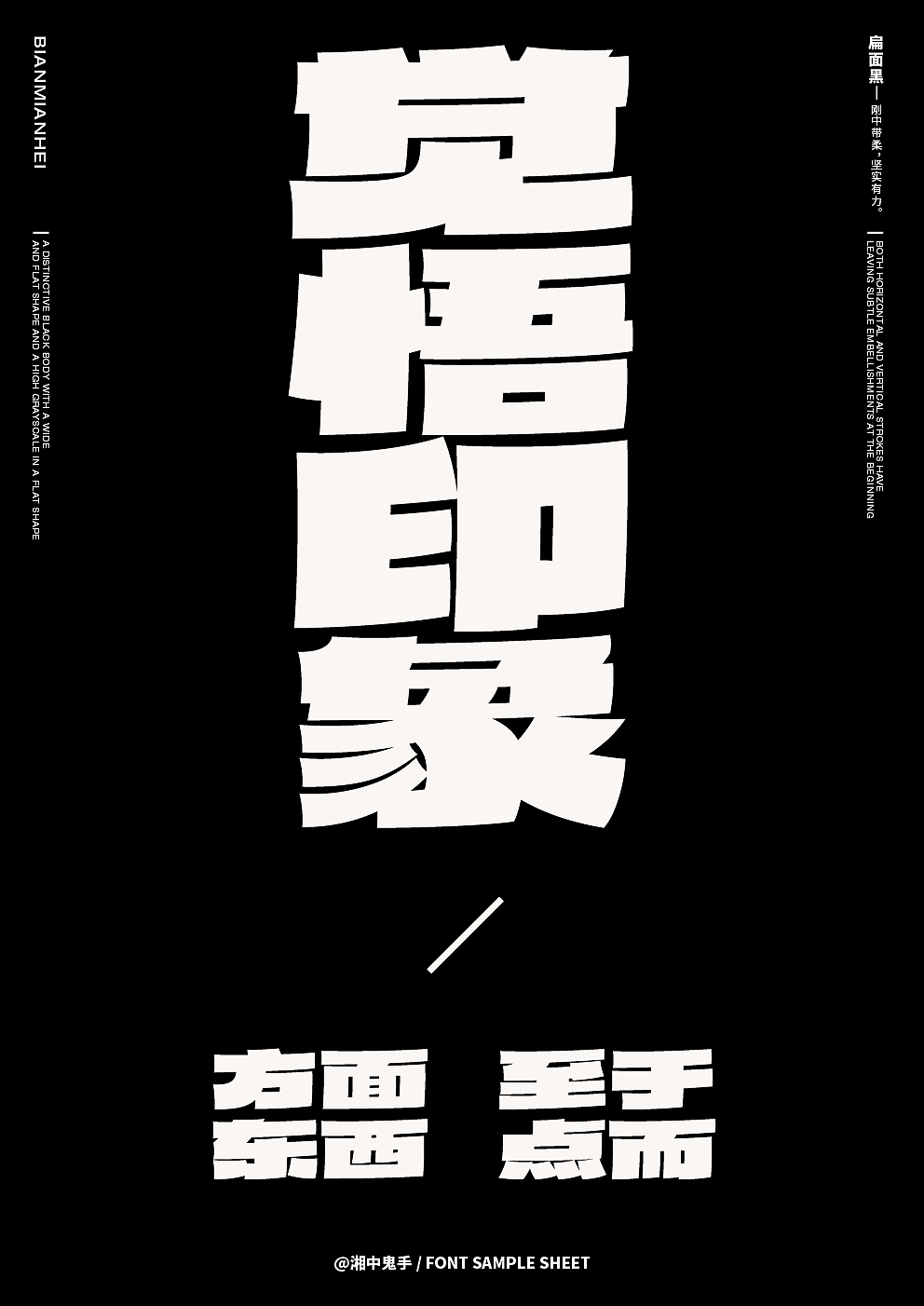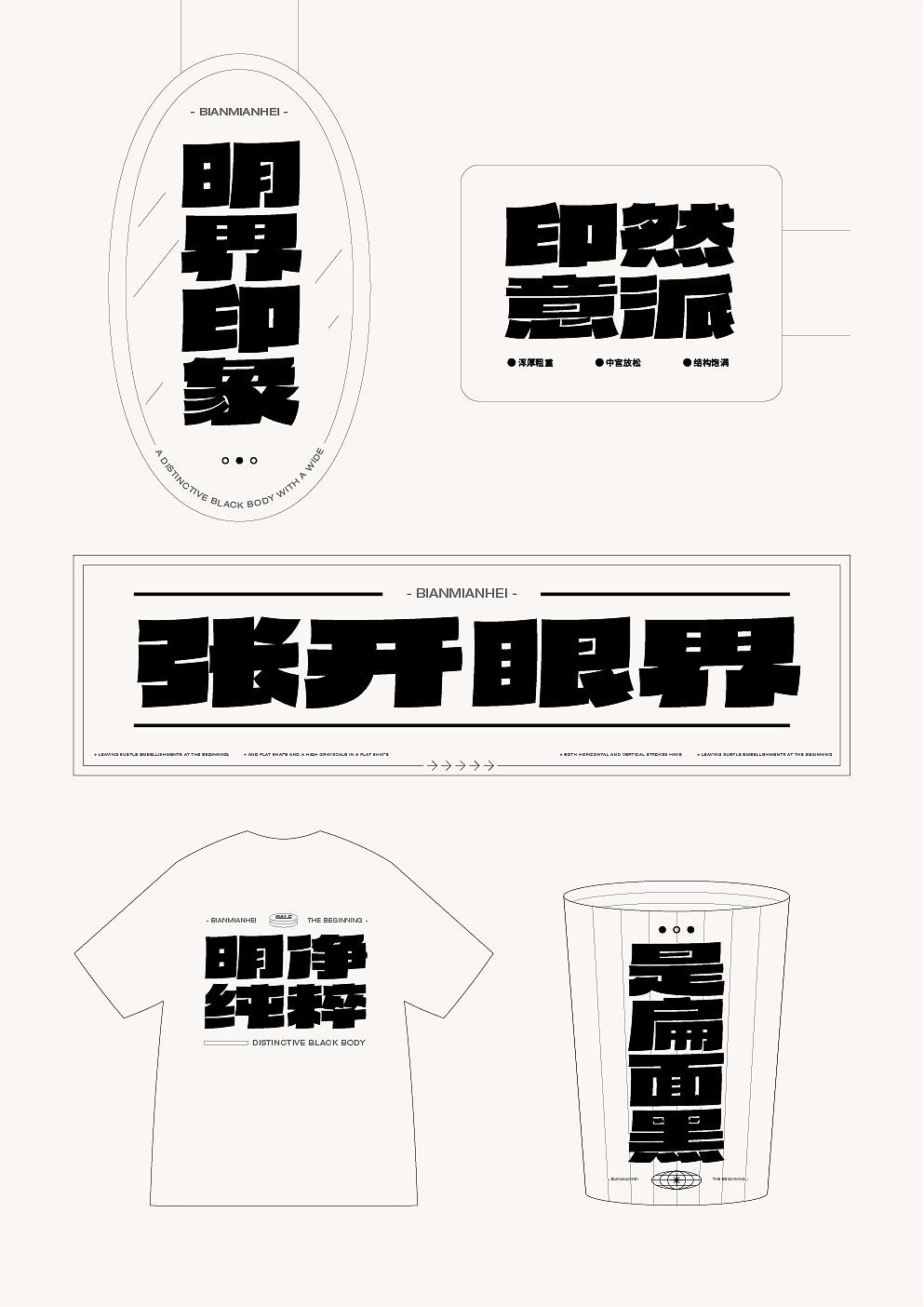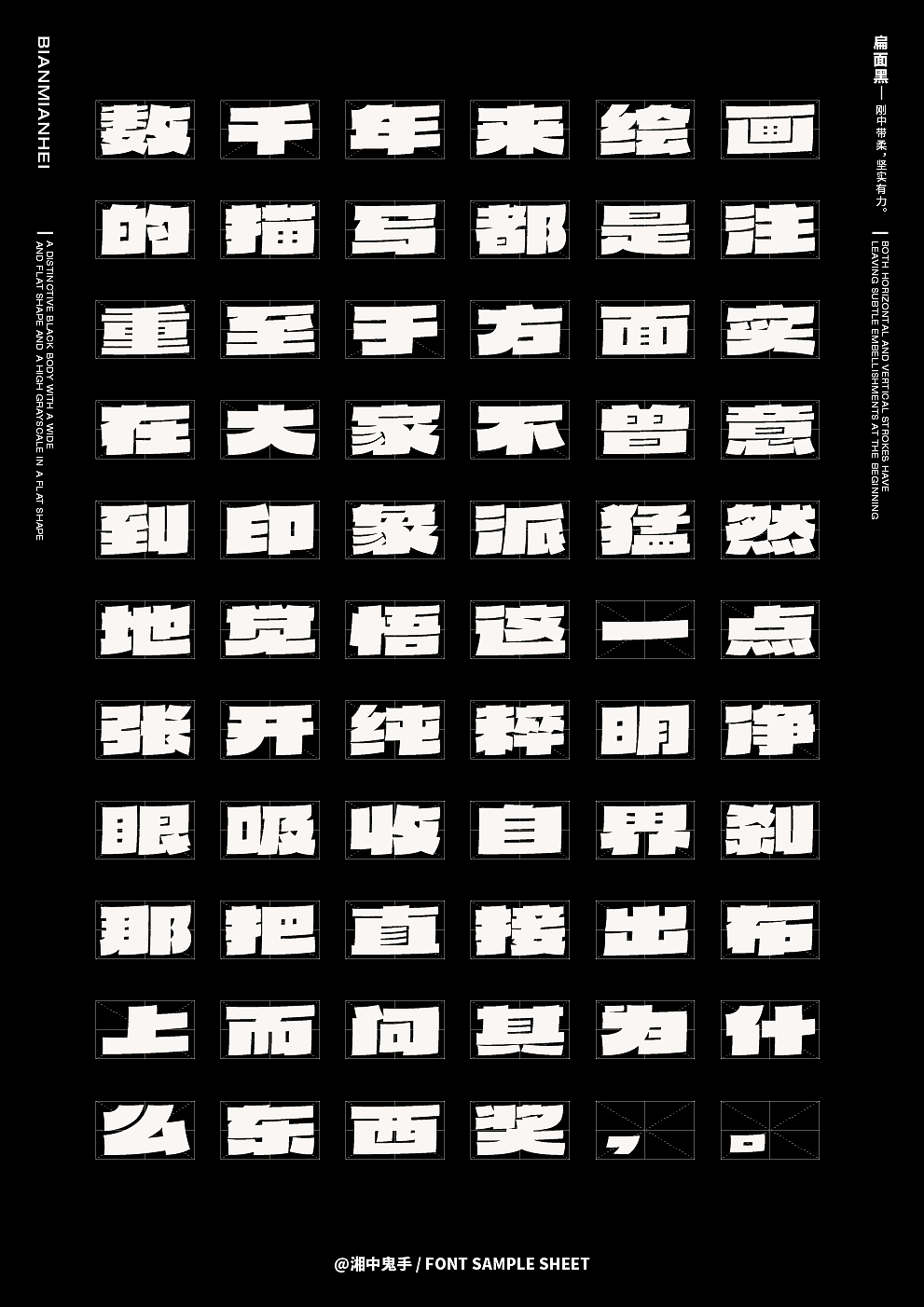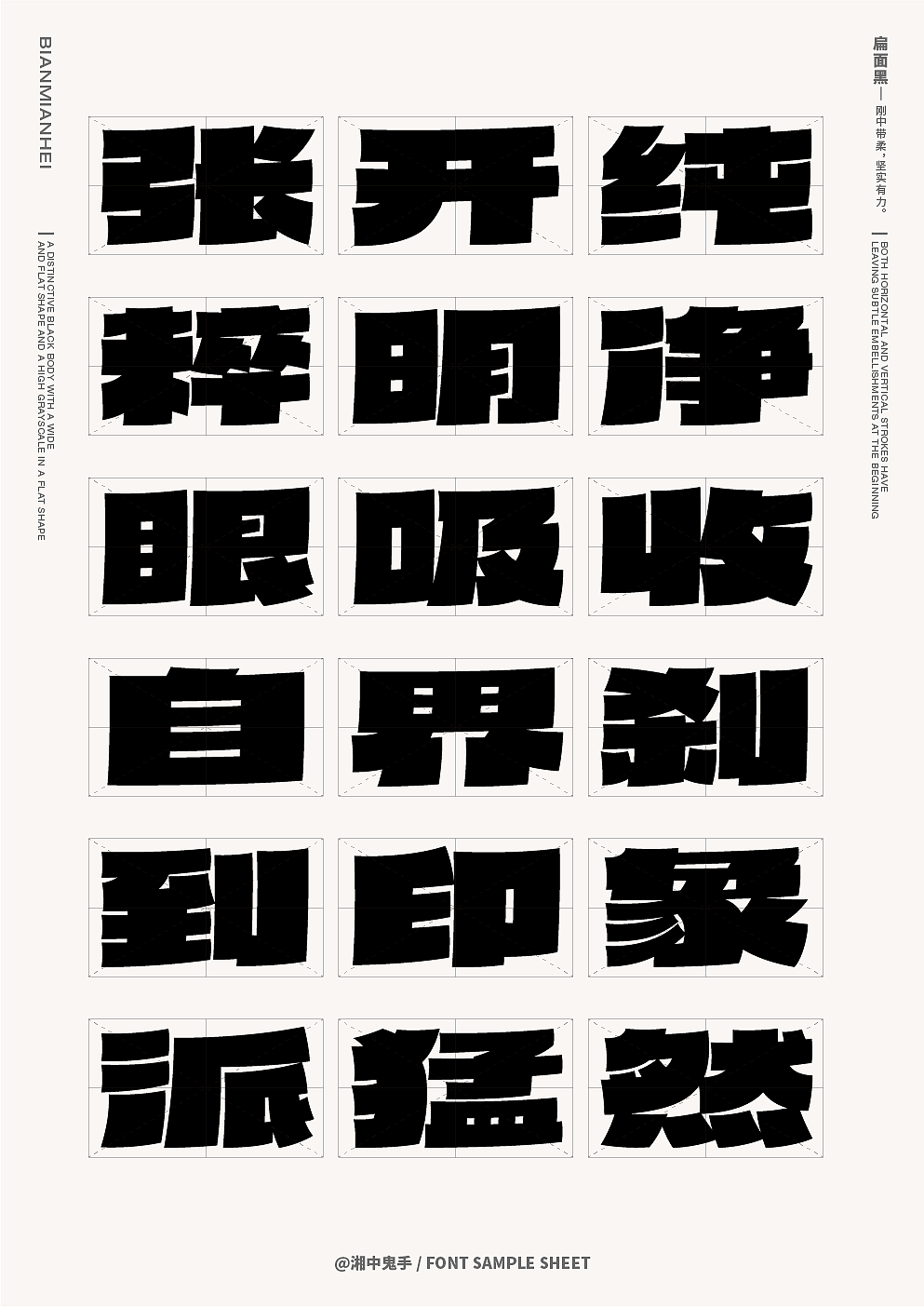
第12届『方正奖』中文专业组金奖:《扁面黑》
《扁面黑》
扁面黑是一款个性鲜明的黑体,其字形宽扁,灰度较高成面状,所以取名扁面黑;横竖笔画都略带曲线,起笔留有细微饰角,横竖笔画微微倾斜,整齐中平添一丝灵动,笔画浑厚粗重,中宫放松,字面大,结构饱满;字形风格新颖,刚中带柔,坚实有力,异常醒目。
@第十二届『方正奖』设计大赛中文专业组金奖